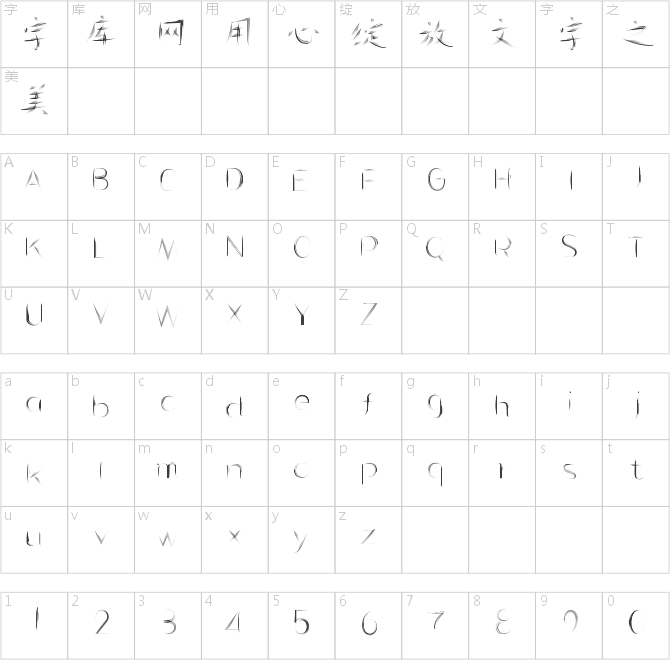
倉(cāng)耳花語(yǔ)
倉(cāng)耳花語(yǔ)字體字庫(kù)是一款讓人賞心悅目、百看不厭的中文字體,適合各類廣告和產(chǎn)品包裝設(shè)計(jì)應(yīng)用,字體大小21.84MB,格式為ttf字體,上傳用戶是ㄚòひ慬偶鰢,作者/版權(quán)方為倉(cāng)耳字庫(kù)